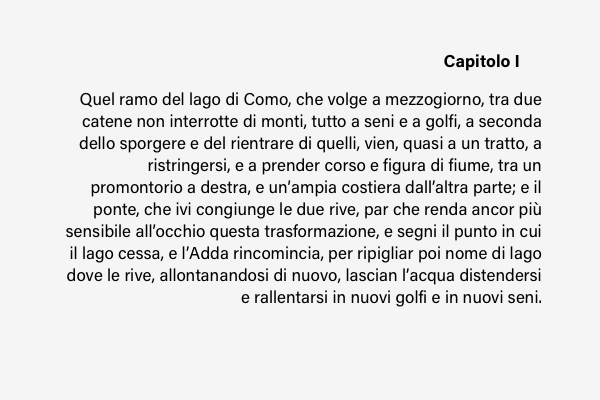
Creare grafica chiara per la stampa: Il font
Dopo layout e colore parliamo del testo tipografico.
Dopo layout, colore e affrontiamo il testo tipografico. Il terzo articolo per aiutarvi a realizzare una grafica a prova di stampa grazie al sapiente uso dei font.
La tipografia è un elemento di progettazione grafica spesso dato per scontato. Per molti grafici è quasi una formalità che si riduce alla scelta di un font. Eppure, se la scelta del font è importante, lo è ancora di più la disposizione del testo nello spazio. La distribuzione corretta e bilanciata delle parole, infatti, gioca un ruolo fondamentale per realizzare una grafica esteticamente curata e con informazioni chiare e leggibili.
Una buona composizione tipografica aiuta il lettore a concentrarsi sul messaggio piuttosto che sui meccanismi di lettura. Al contrario, una cattiva tipografia distrae.
Cosa succede quando leggiamo un testo?
Capire come leggiamo e vediamo un testo è utile per organizzarlo e introdurlo correttamente nel file grafico. La lettura di una riga di testo avviene a scatti. Questi scatti si chiamano “saccadi”.  Quindi i nostri occhi compiono diversi “scatti” avanti e indietro nel testo, analizzando la riga con varie saccadi. Tra una saccade e l’altra avviene quella che è chiamata “fissazione”, il momento in cui assorbiamo l’informazione della parola. L’ampiezza di una saccade è di 5-10 caratteri, circa 1-2 parole (se consideriamo un carattere di media grandezza, come quello dei libri). Nella lettura, la visione d’insieme ha un ruolo importante nel fornire indicazioni alle saccadi[1].
Prima guardiamo e poi leggiamo.
La tipografia svolge un doppio ruolo in qualità di comunicazione verbale e visiva; infatti man mano che i lettori analizzano una pagina, sono inconsciamente consapevoli di entrambe queste funzioni: per prima cosa studiano i modelli grafici generali della pagina e poi analizzano il linguaggio leggendo il testo[2].
L’ampiezza delle saccadi e i tempi di fissazione dipendono dall’esperienza del lettore e dalla familiarità che ha con il testo. Se leggiamo un testo scientifico, e non siamo addetti ai lavori, resteremo più tempo a fissare una parola oppure la rileggeremo più volte per capire il senso della frase.
Tra visibilità e leggibilità
Il testo, in un documento stampato (ma anche nel web) sarà tanto più efficace quanto più riuscirà ad essere individuato e letto facilmente. Quando si parla di lettura di un testo bisogna distinguere tra visibilità e leggibilità.
La visibilità (legibility) indica quanto un testo può essere individuato facilmente per chiarezza, contrasto, illuminazione.
La leggibilità (readability) riguarda invece la facilità di lettura e il grado di affaticamento.
Scriveva Stephen Coles di Typographica, in un tweet di qualche tempo fa riguardo alla leggibilità (readability):
Il termine readability non richiede semplicemente “Puoi leggerlo?” o “Quanto velocemente puoi leggerlo?” Chiede anche “Vuoi leggerlo?”.
Visibilità e leggibilità ci aiutano a comprendere che il testo non solo deve essere individuato in maniera nitida nella composizione, ma deve anche essere accattivante agli occhi del lettore. Per ottenere questo risultato entrano quindi in gioco diverse variabili, come:
• collocazione corretta del testo nello spazio
• gerarchizzazione delle informazioni
• scelta dei caratteri tipografici
• scelta delle parole chiave
• capacità di sintesi e di chiarezza delle informazioni
• tono di voce e stile del testo
In questo articolo, ci occuperemo in modo particolare di:
• collocazione corretta del testo nello spazio
• scelta corretta dei caratteri tipografici
• gerarchizzazione delle informazioni
Eppure, ci sono altri elementi da tenere in attenta considerazione, che riguardano più la scelta dei contenuti e il valore delle parole in senso stretto. Le valutazioni che riguardano i contenuti sono altrettanto importanti per stimolare il lettore e indurlo a soffermarsi sul testo e ad individuare le informazioni fondamentali a colpo d’occhio. Per questo motivo è utile la collaborazione con un copywriter, oltre al grafico, per garantire la scelta delle informazioni e la stesura migliore dei testi che compariranno sul materiale stampato.
Gli elementi del testo: disporli correttamente nel layout
Quando un lettore si avvicina a una rivista, una brochure, un catalogo o un volantino, per prima cosa guarda l’insieme degli elementi che lo compongono. Vede come interagiscono tra loro e poi comincia a leggere, scorrendo la pagina fino a quando non trova qualcosa che lo interessa. È importante, quindi, che sia chiara la correlazione tra gli elementi testuali e che tale correlazione sia facile da individuare al primo sguardo.
Nelle immagini che trovate di seguito, si vede come piccolissime modifiche possono cambiare la percezione del testo e del layout.
Nella prima immagine non riusciamo a distinguere correlazioni, i quattro paragrafi potrebbero essere correlati oppure separati, lo possiamo scoprire solo leggendoli.
• Il contrasto si può ottenere anche con l’opporre pesi (light/bold) o larghezze (regular/condensed o extended).
La tipografia non è un’arte. La tipografia non è una scienza. La tipografia è un mestiere, non nel senso della cieca osservazione di regole incomprensibili, ma mestiere nel senso dell’utilizzo di solide esperienze verificate. [1]